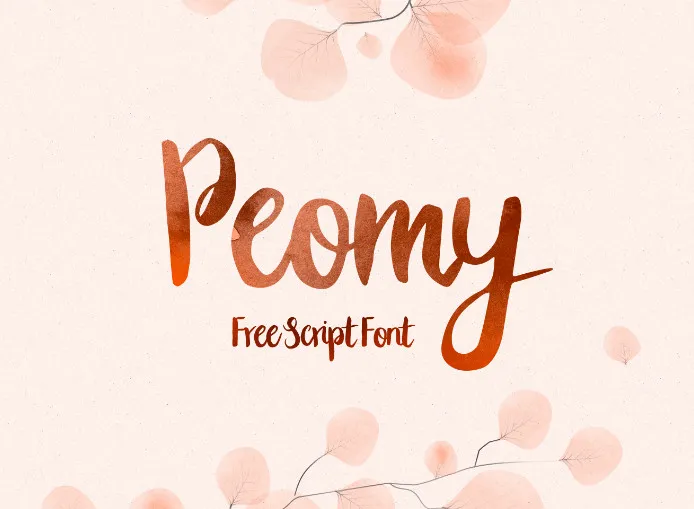
Peomy Script Font – Fonte Grátis
Peomy Script Font
A Peomy Script Font é uma obra-prima para quem busca estilo e personalização em cada design. Ela foi criada por Krisjanis Mezulis com a fina arte da escrita aquarelada, utilizando um fude-brush repleto de tinta preta pesada sobre papel pastel branco e claro. O resultado é uma fonte com traços suaves e elegantes, perfeitamente adaptada para conceitos únicos e personalizados. A Peomy Script Font é caracterizada por seu estilo de escrita única e autêntica, oferecendo uma grande variedade de caracteres em maiúsculas. Essa fonte não inclui minúsculas ou caracteres especiais, mas isso também contribui para um design limpo e elegante. Com 385 letras em caps, a Peomy Script Font é ideal para criar textos memoráveis e distintivos que chamam atenção. Este design de escrita aquarelada não apenas oferece um aspecto impecável para uso em materiais gráficos digitais, mas também tem o poder de transformar qualquer projeto no qual seja aplicado. Para aqueles que buscam algo diferente e singular na fonte de escrita digital, a Peomy Script Font é uma escolha inteligente.